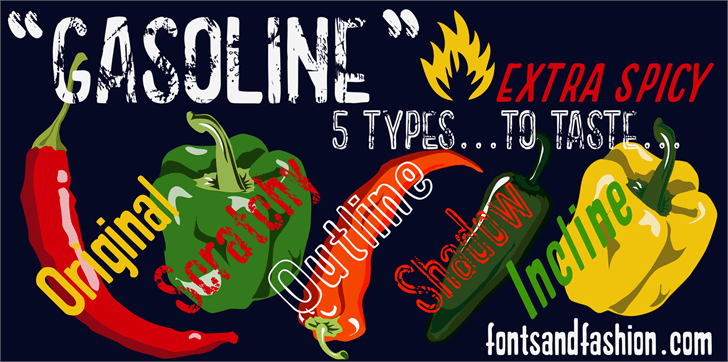
Descubra a graça do Gasoline Scratchy Font com esta categoria de Sans Serif disponíveis nas páginas oficiais de Fontsandfashion. Inspirada na cultura urbana, essa fonte dá um toque único às suas criações digitais. O designer Hamilton criou o Gasoline Scratchy Font, que adiciona um ar dinâmico e descontraído a qualquer projeto gráfico. Ideal para elementos como headlines e design de interfaces de usuário, esta fonte incorpora nuances inspiradas na cultura da rua com um toque minimalista e moderno. Navegue pelas páginas de Fontsandfashion em seu próprio estilo, onde encontrará uma variedade de outras opções de fontes. Para manter-se atualizado sobre novidades e recursos exclusivos, siga-nos nas redes sociais: Facebook e Pinterest. Seja criativo e transforme o digital no ritmo da moda!